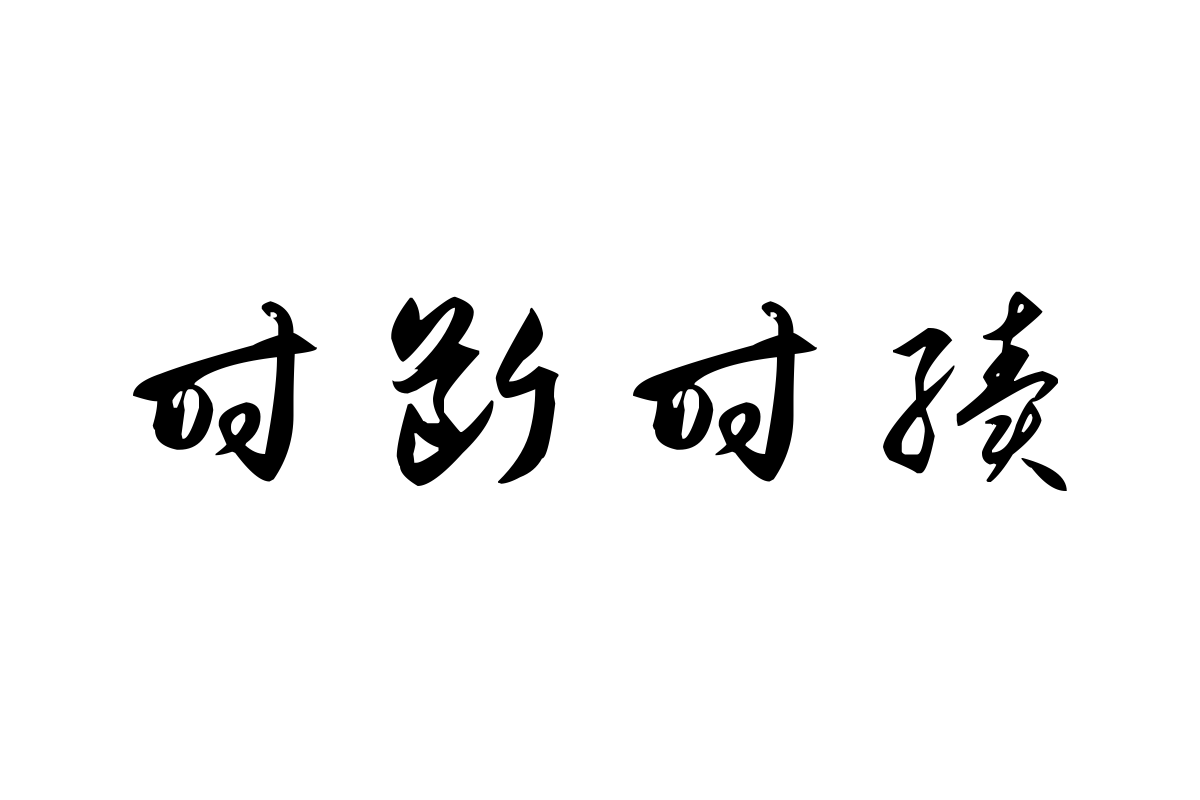
张平草书字体是汉呈公司推出的一款书法风格字体,其特点是笔画流畅、结构紧凑,具有很高的艺术价值和实用性。张平草书字体在设计上注重线条的粗细变化,使得字体看起来更加生动有趣。同时,该字体还采用了一些特殊的排版技巧,如将字间距调整为一定的比例,使得整体视觉效果更加协调。
总的来说,张平草书字体是一款非常优秀的书法风格字体,无论是用于网页设计还是印刷品制作,都能展现出独特的艺术魅力。